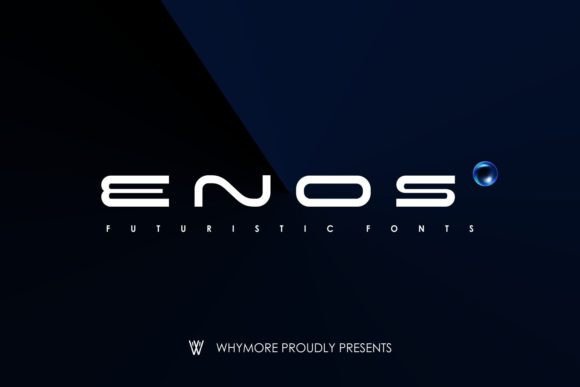
Enos
適切なデザイン要素を見つけるのは難しい場合がありますが、Enosは作品を即座に引き立てる優れたコレクションを提供します。
精密に作られたEnosは、クリーンなベクター、滑らかなタイポグラフィ、そして安心のための商用ライセンスを提供します。
POD(オンデマンド印刷)製品、結婚式の招待状、またはソーシャルメディアのグラフィックを作成している場合でも、Enosは理想的です。